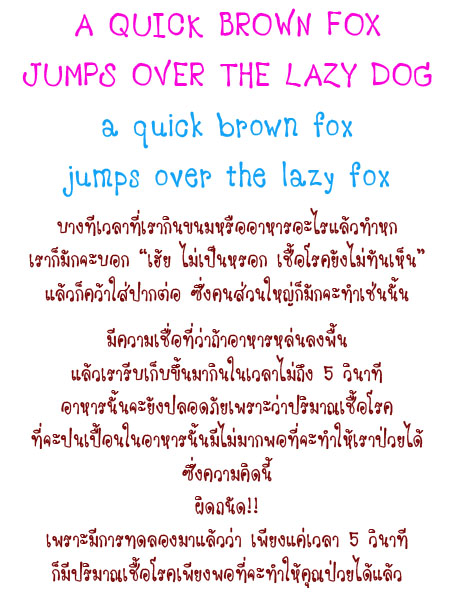
ทําฟ๐นต์ใหม่อีกตัวค่า..
ตามนี้เลยค่ะ
เป็นไงบ้างอ่ะ  :40:
ตามนี้เลย  :22:
ไงมั่งอ่ะคะ
:25: น่าใช้ครับ ฟอนต์มีน้ำหนักแบบนี้เลย
กลัวอยู่แค่นิดเดียวตรง จ จาน เอาตูดมันลงมาอีกนิดนึงได้ไหมครับ
ถ้ากลัวจะเสียดีไซน์ก็เอาลงนิดเดียวพอ เพราะถ้าดูโดดๆ ไม่รวมกันมากมันจะเนียนคล้ายกะ ล ลิงจ้ะ
ทำฟ้อนต์ใหม่อีกแล้วเหรอ?
:45: ขยันมากเลยค่ะ
พี่แอน แก้ จอ จานแล้วนะ โอเคขึ้นมั้ย?
น่ารักน่าใช้ มากเลยจ๊ะ :12: :12:
น่ารักจังครับ ( คนทำด้วย )  :10: